"BÍ KÍP" CẦN NHỚ KHI SỬ DỤNG FONTS CHỮ TRONG THIẾT KẾ
Một dự án thành công nhiều hay ít phụ thuộc phần lớn vào typography. Ngoài việc đáp ứng các yếu tố về mặt thẩm mỹ thì font chữ trong thiết kế cần phải đáp ứng những yêu cầu nhất định về mặt kỹ thuật và chức năng.
Để có thể dùng fonts thật “lợi hại” thì bạn không nên bỏ qua những “bí kíp” dưới đây. 3DKID tin rằng, nếu bạn có thể khéo léo kết hợp các fonts chữ với nhau, thiết kế của bạn sẽ cực kì ấn tượng đó nha!
1. FONT CHỮ PHẢI RÕ RÀNG, DỄ ĐỌC
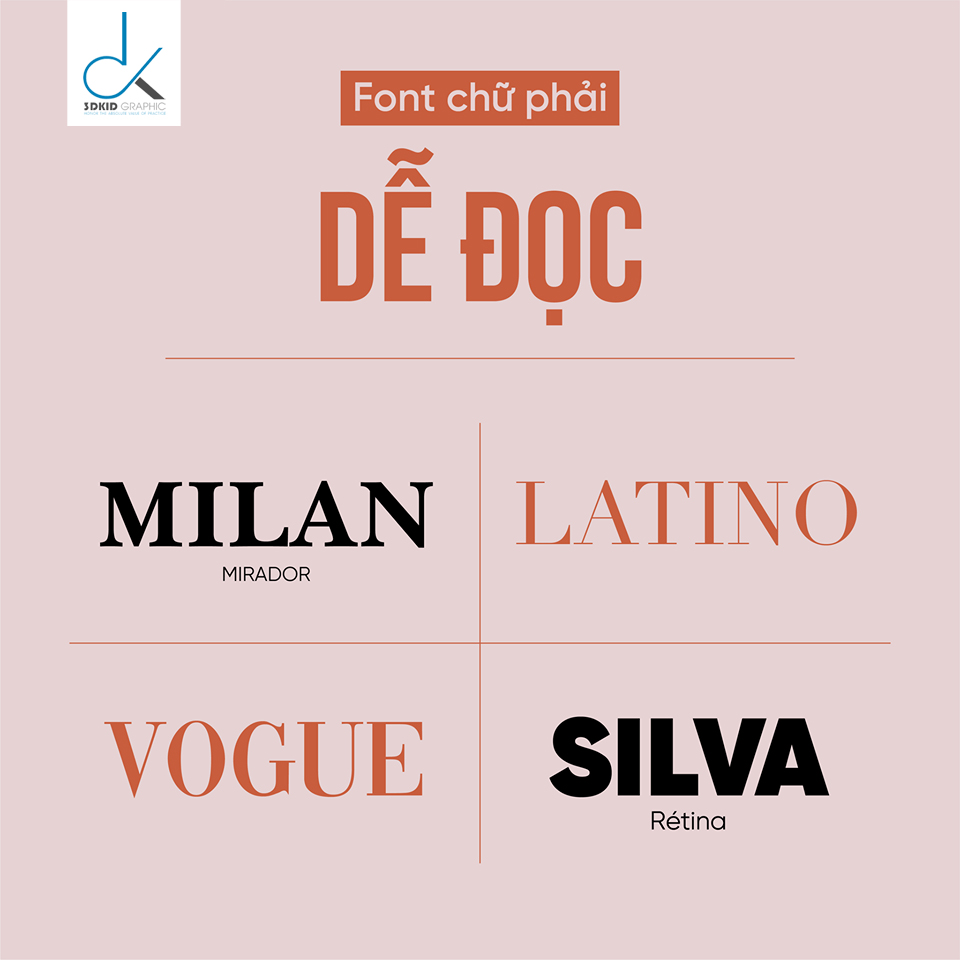
Một font chữ đẹp, ấn tượng nhưng lại rối mắt sẽ khiến người đọc bị rối và khó nắm bắt được thông điệp mà ấn phẩm muốn truyền tải.
2. PHÙ HỢP VỚI ẤN PHẨM, NGƯỜI ĐỌC
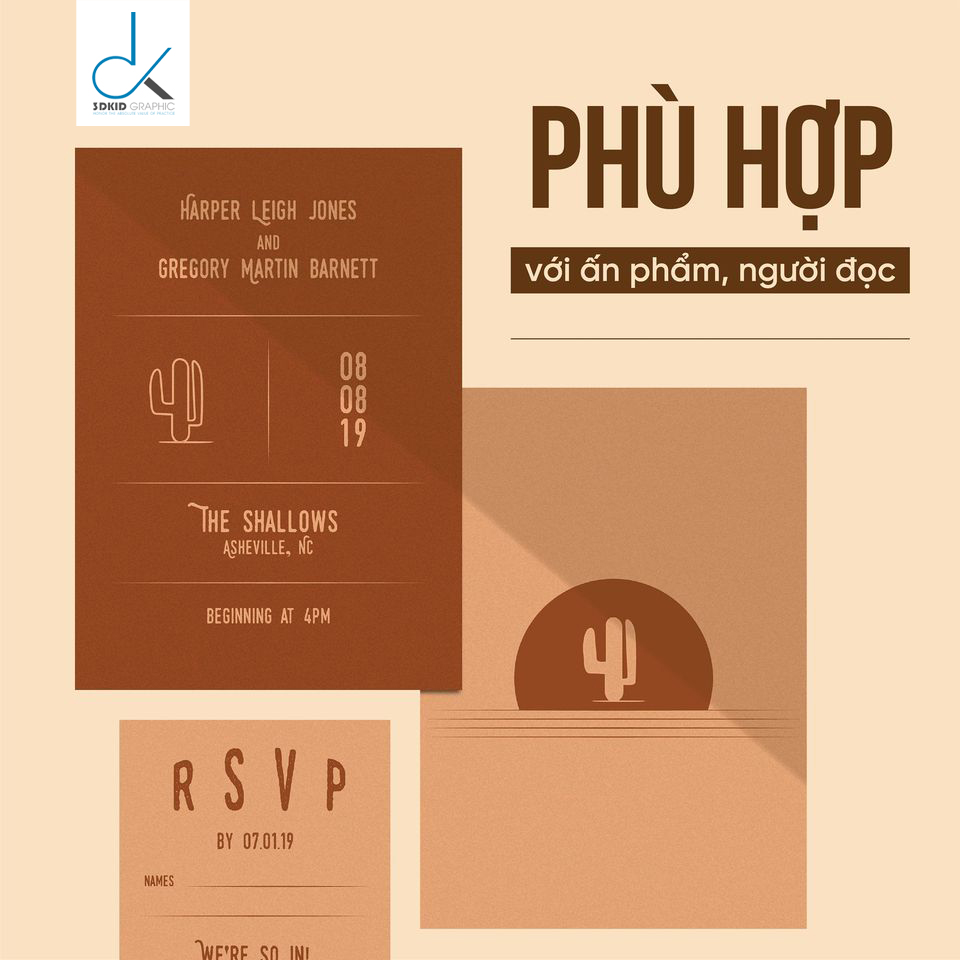
Font chữ dù đẹp đến mấy mà lại không phù hợp với mục đích của ấn phẩm hay người đọc thì cũng vô ích. Một ấn phẩm cần sự nghiêm túc, trang trọng thì dùng font chữ vui nhộn, nhắng nhít là một điều không nên đâu.
3. TẬN DỤNG KHOẢNG CÁCH ĐỂ TẠO SỰ ẤN TƯỢNG
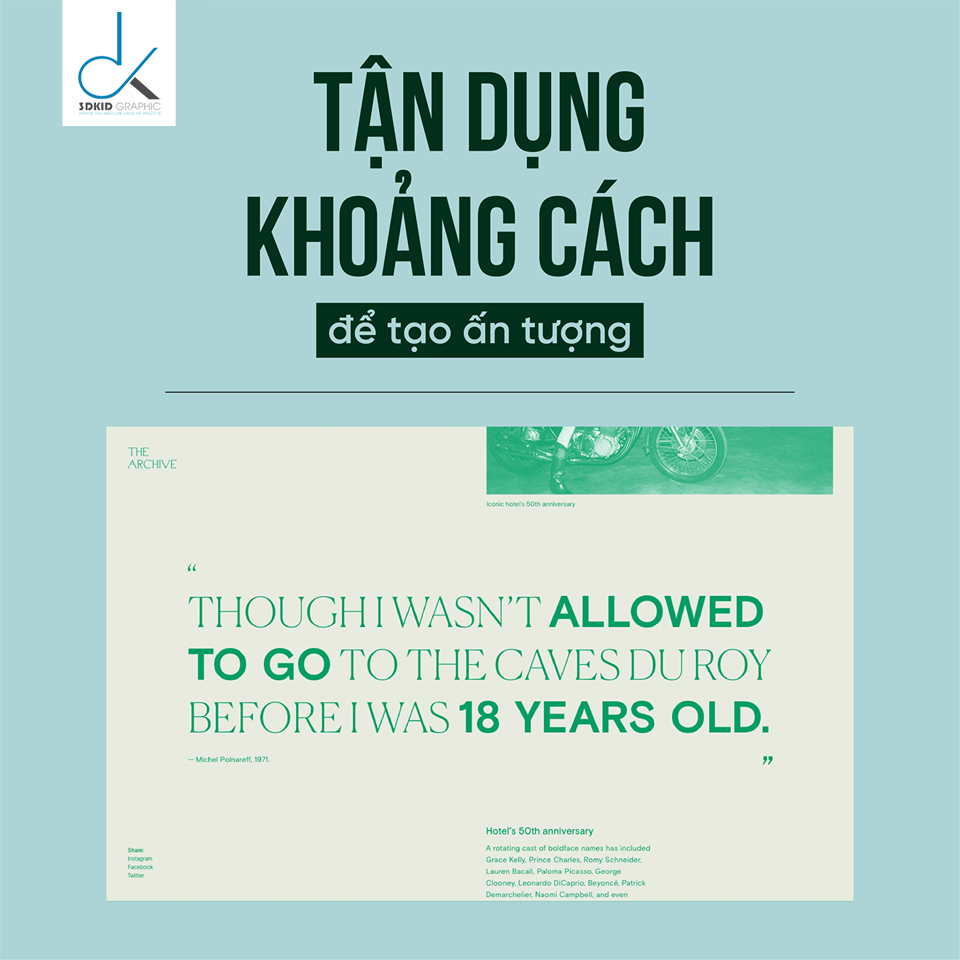
Việc tận dụng khoảng cách trong thiết kế là rất quan trọng. Những “khoảng trống” trong ấn phẩm của bạn sẽ khiến cho người đọc cảm nhận và ấn tượng theo mỗi cách khác nhau. Hãy tạo ra một hệ thống phân cấp thông tin để người đọc dễ dàng tiếp thu được những điều mà bạn muốn truyền tải.